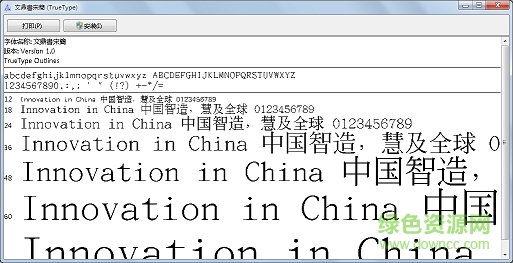
gbinnming-medium
gbinnming medium字體又叫文鼎書宋字體,線條舒展,文雅秀美,適讀性出色,帶有古典氣息,適合用于各類印刷排版中,而且在本站下載的字體都是可以永久免費(fèi)使用的哦,喜歡的朋友快來綠色資源網(wǎng)下載吧!
gbinnming medium字體特點(diǎn)
1.線條簡(jiǎn)潔流暢,筆形規(guī)范、嚴(yán)謹(jǐn),強(qiáng)調(diào)秩序感、平衡感;
2.字面大小勻稱、行氣貫通,灰度均勻,呈現(xiàn)一種整齊的、矩陣式的形式美感,
3.有放松自然的感受,使得閱讀效果更為流暢。